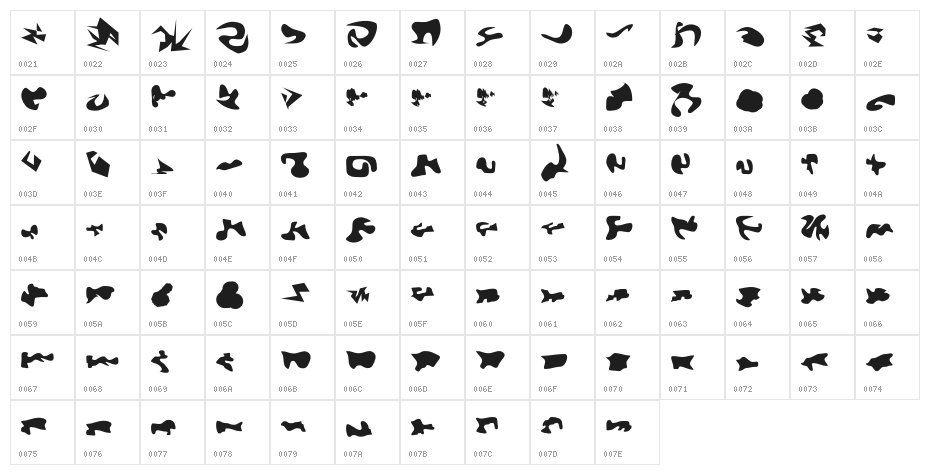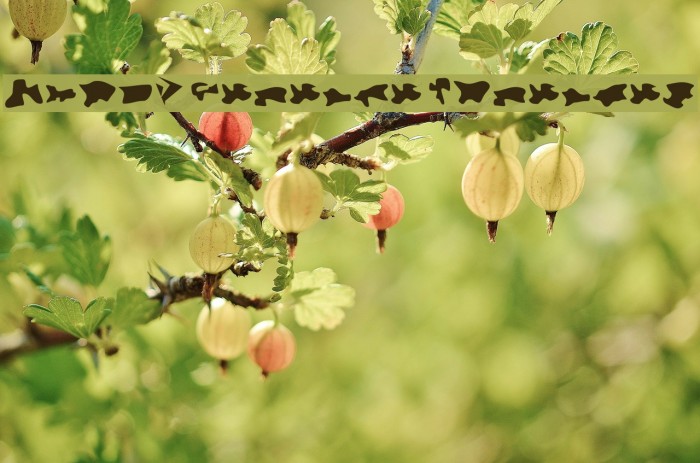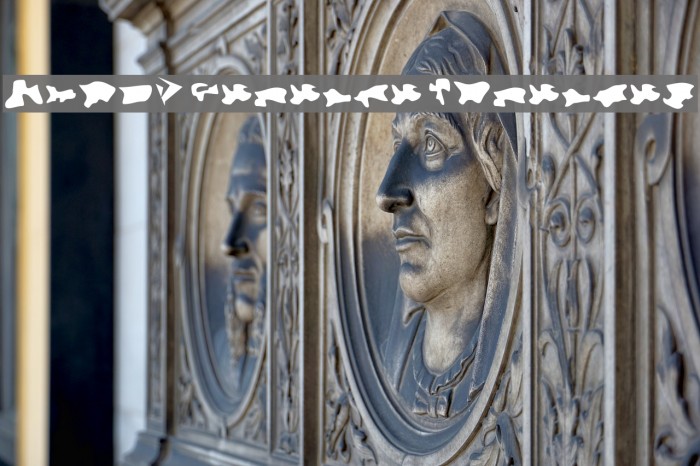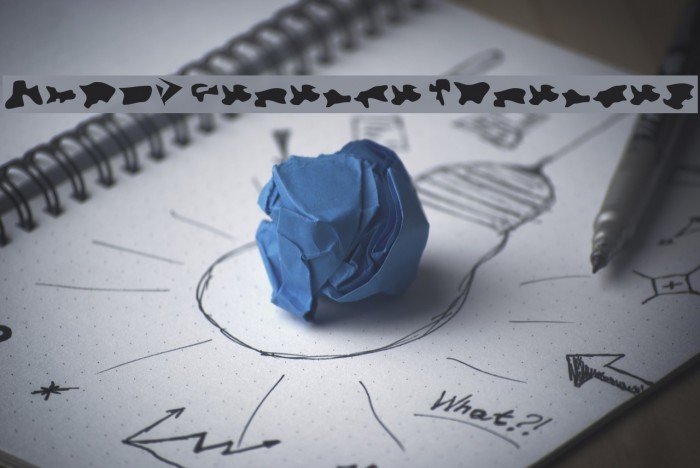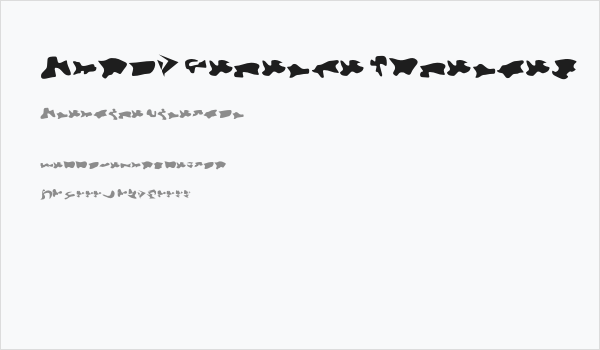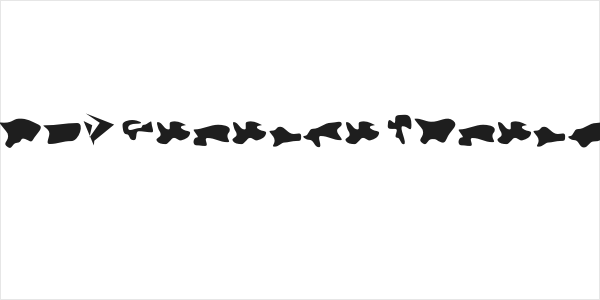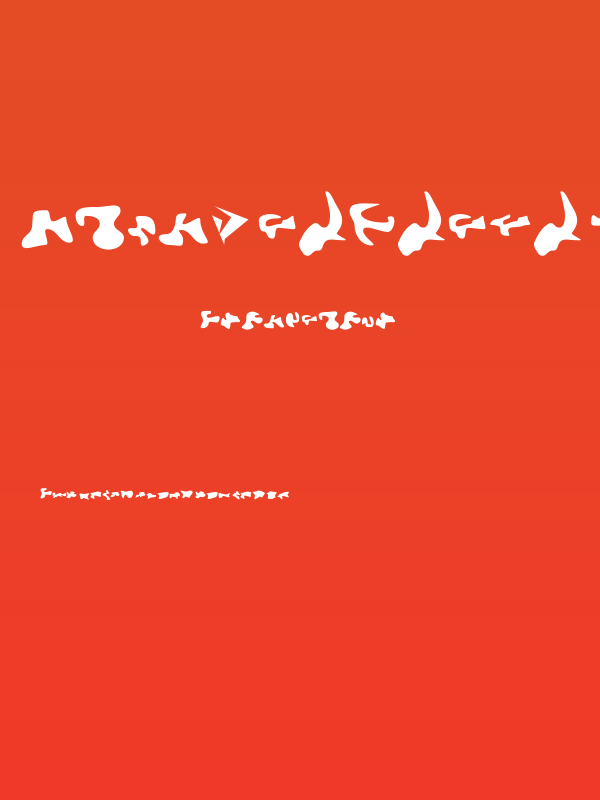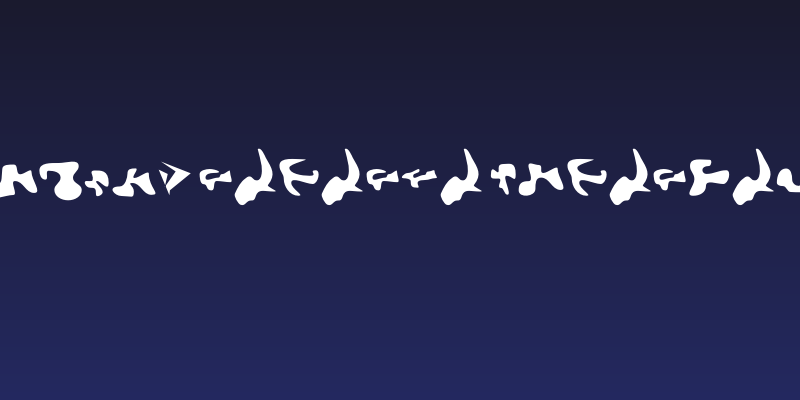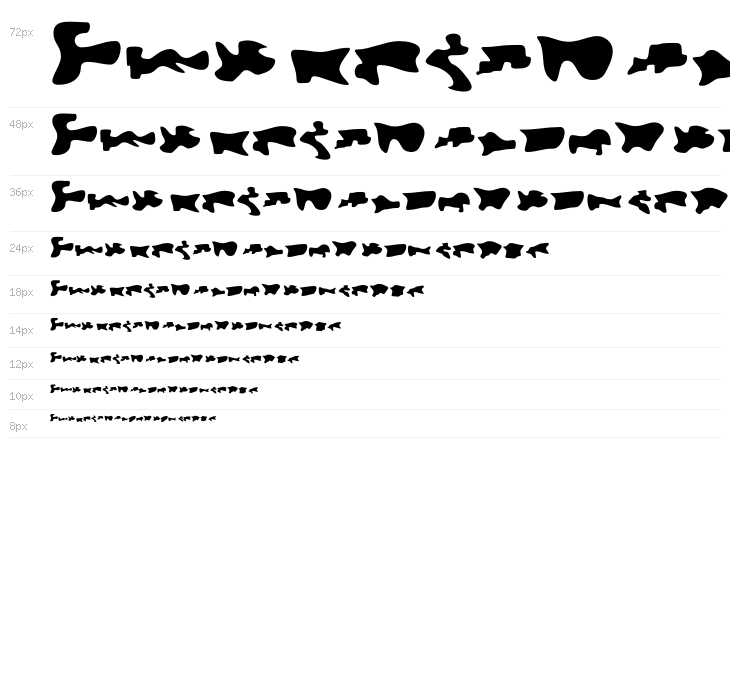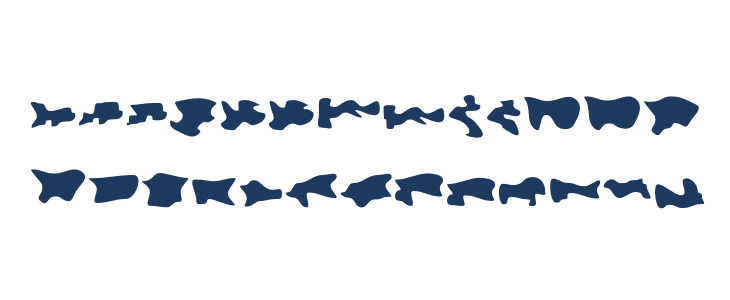
Camo3 Reverse Inverted Font
| Caso d'uso | Logos, Art projects, Experimental designs |
| Progetti proposti | Ideal for artistic projects, abstract art pieces, experimental design work, and creative branding where visual impact is key. |